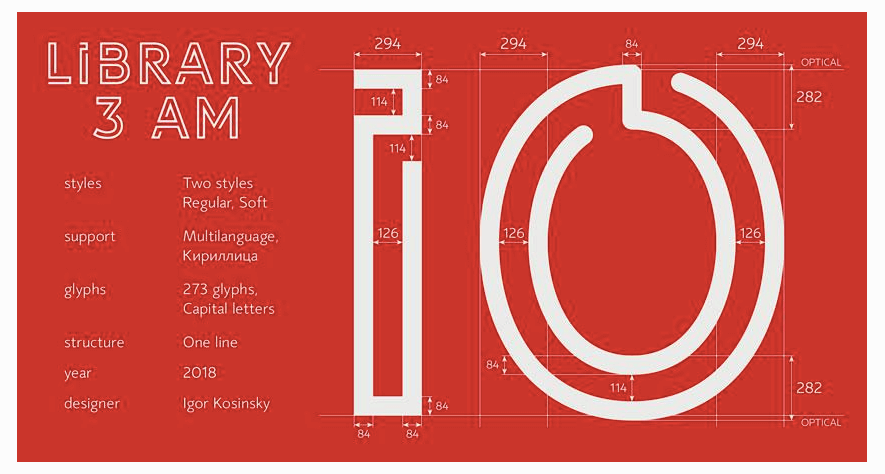
【厳選20選】個人および商用向けデザイン用無料アウトラインフォント
注目を引き目立つデザインとしたい場合は、アウトラインフォントの使用を検討しましょう。これらのフォントは、ロゴやブランディングプロジェクトだけでなく、広告やWebサイトのヘッダーにも使用できます。
場合によっては、ネオンテキスト効果を適用して、美しく魅力的なポスター、名刺、看板などを作成することもできます。
オンラインで入手可能なアウトラインフォントは非常に優秀です。高品質のアウトラインフォントは無料で、商用プロジェクトと個人プロジェクトの両方で使用できます。
このまとめでは、無料でダウンロードできる最高のアウトラインフォントを集めました。これらは、さまざまなプロ、ブランディング、およびビジネスグラフィックデザインで使用できます。
Library 3am Font Family
Library 3amには2つのスタイルと合計273のグリフがあります。多言語サポートがあり、大文字、記号、数字が含まれています。このフォントは、個人および商用での使用が無料です。
Elephant Font
Elephantフォントは、大文字、数字、記号を含む太字のサンセリフ体です。制限なしで、個人プロジェクトと商用プロジェクトの両方に使用できます。
Robinson Outline Font
ロビンソンフォントは、ビンテージの新聞のタイトルに触発されました。これは、雑誌やポスターを念頭に置いて特別に作成された、すべて大文字のフォントです。フォントには、斜めのバリアントも含まれます。
Argon Outline Font
Argonフォントは、文字が迷宮に似ている現代的で創造的なフォントです。フォントには大文字と数字が含まれます。無料版は個人プロジェクトに使用できます。
Fakedes Outline Font
Fakedesは丸みのあるセリフフォントで、より大胆な外観を要するロゴやブランドプロジェクトに最適です。フォントには、大文字と小文字、記号、数字が含まれ、多言語サポートが含まれています。
Gibsons Outline Font
Gibsonsフォントファミリには、20のフォントと3つのウェイトが含まれています。さまざまなプロジェクトと4つの異なるスタイルに適しています。このフォントは、Envato Elementsサブスクリプションの一部として提供されます。
Frontage Free Font
Frontageは、5種類のスタイルを持つレイヤー化された書体システムです。このフォントはさまざまなプロジェクトで使用でき、さまざまなスタイルを組み合わせて独自のデザインを作成できます。
The Champ Font Family
このアウトラインフォントは、個人プロジェクトで自由に使用できます。このフォントは、重厚な外観で、4つの異なるスタイルがあります。
Brixton Sans (Fill and Outline)
Brixton Sansには、塗りつぶしとアウトラインの2つのバージョンがあります。アウトラインバージョンは、独自の洗練された外観を必要とするブランディングまたはデザインプロジェクトに最適です。このフォントは、Envato Elementsサブスクリプションの一部として利用できます。
Paralines Font
Paralinesフォントは、レトロで未来的な雰囲気のオールキャップフォントです。商用プロジェクトと個人プロジェクトの両方で使用できます。
Ostrich Sans Inline Font
Ostrich Sansフォントは、個人プロジェクトおよび商用プロジェクトで使用できます。フォントには、大文字、記号、数字が含まれています。
Hikou Outline
ネオン効果がよく似合うフォントを探している場合は、Hikouフォントが最適です。フォントはEnvato Elementsからダウンロードでき、多言語の大文字、数字、句読点が含まれています。
Neon Font
ネオンフォントは、ネオン効果が適用された場合にうまく機能する別のフォントです。このフォントは、個人および商用での使用が無料です。2つのスタイルがあり、大文字、数字、句読点が含まれます。
Еasy Outline Font
Easy Outlineフォントは、個人プロジェクトおよび商用プロジェクトに使用できます。薄くて背が高いフォントなので、ファッションや美容デザインのプロジェクトに最適です。
Portico Outline
このフォントは、ネオン看板に最適です。Envato Elementsサブスクリプションの一部として無料でダウンロードできます。
Anthology Font
Anthologyフォントには5つの異なるスタイルがあり、完全な多言語サポートがあります。フォントは個人プロジェクトで自由に使用できます。また、このフォントに最適なボーナスベクトルアイコンが表示されます。
Halfomania Font
これは、個人用および商用のプロジェクトで使用できる未来的なサンセリフフォントです。大文字と小文字、数字、句読記号が含まれています。
Burford Rustic Outline
素朴で風化した外観を必要とするプロジェクトには、このフォントが最適です。Envato Elementsサブスクリプションの一部としてダウンロードできます。フォントには、20のフォントファイルと3つの異なるフォントスタイルが含まれています。
Potra Typeface
Potraフォントには、大文字、数字、句読記号があります。個人および商業プロジェクトで使用でき、丸みを帯びています。
Montana Bold Outline Font
Montanaは、表示目的に適した丸い書体です。大文字と小文字の両方があります。
Darling Bloom Font
手描きのアウトラインフォントを探している場合は、Darling Bloomフォントを試してください。エレガントなプロジェクトやフェミニンなブランディングに最適です。このフォントは、Envato Elementsサブスクリプションの一部です。
Batter Up Outline Font
シンプルなアウトラインフォントが必要な場合は、Batter Upが役立ちます。ユニークな外観で、大文字のみが含まれています。このフォントは、個人および商用での使用が無料です。
NeoRetroDraw Font
この表示フォントは、個人および商用プロジェクトで制限なしで使用できます。フォントはレトロな外観で、3つの異なるスタイルがあります。
VISIA Duo (Natural & Outline) – Geometric Typeface
このフォントデュオには、通常のsans-serifフォントとアウトラインsans-serifフォントが含まれています。Envato Elementsにサインアップすると、4つの太さのフォントをダウンロードできます。
Geometrica Hand Font
名前が示すように、このフォントは幾何学的な手描きの外観を持っています。レトロなプロジェクトに最適です。このフォントは個人での使用が無料です。
Amorica Font Family
このフォントファミリには4つのフォントが含まれ、大文字と小文字、数字、記号が含まれています。このフォントは個人での使用は無料です。
Neoneon Font
これは、ネオンの外観が必要な場合は別の素晴らしい選択です。このフォントは、大きなヘッダー、ポスター、さらには看板に最適です。個人および商用での使用は無料です。
Altero Solid & Outline Font
Alteroは、ソリッドフォントとアウトラインフォントを備えた別のフォントデュオです。個人および商用での使用は無料です。大文字、数字、句読点記号が付いています。
デザインに特別なタッチを追加する必要がある場合は、アウトラインフォントが必要な場合があります。アウトラインフォントは汎用性があります。背の高い薄いアウトラインフォントを選択すると、洗練された外観が必要な任意のデザインで使用できます。ネオン効果で見栄えの良いフォントを選択すると、効果的なポスターや看板を作成できます。この記事で紹介するアウトラインフォントを使用して、リソースライブラリを拡張します。